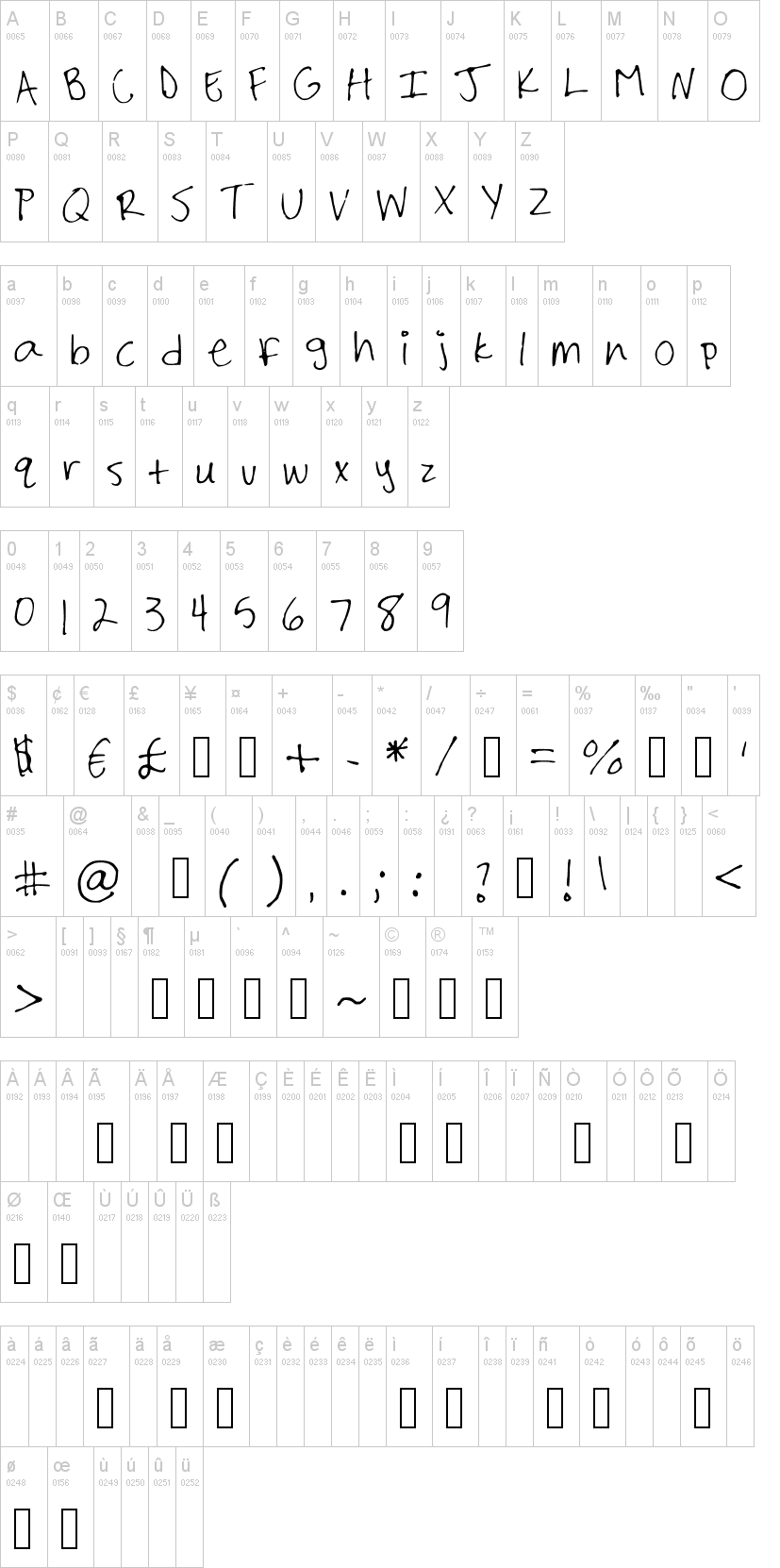
Shailene Marks 是一款简洁的字体,由英国设计师 Shailene Marks 创作。这款字体以现代感和柔和的线条为特点,让文本看起来更加简洁,同时又不失优雅。它可以用来制作标题、标签、海报、网页、印刷品等,是一款经典的英文字体。内容介绍
Shailene Marks是一款非常不错的手写艺术字体,具有很好的视觉感,适合于文化类的宣传设计、商业类品牌的广告和产品包装设计以及个性化文字排版等较多场景。